在信息化时代,我们被信息包围着,时刻与信息相关联着,传播信息、获取信息成为了人们主要的工作,无论是广告标语、横幅内容、影视节目等等都是在传播信息,人们通过这些也在接收这信息。铺天盖地的信息围绕着人们,如何在这场信息传播赛中取胜仿佛是大家都在思考的事情。接下来,就让义启字库带领大家来看看如何美化大家想要传播的信息。
字作为传播信息重要的元素,自然是免不了人们对它的创造和更新的,人们为了能够让自己的信息得到有效的传播,通常会在字体设计版式上下功夫。各种各样不同的字体会让整个信息变得更加不同,比如你想要传播一个开心快乐的消息,你就可以用一些飘逸的字体去让整个消息变得更具愉快的氛围。
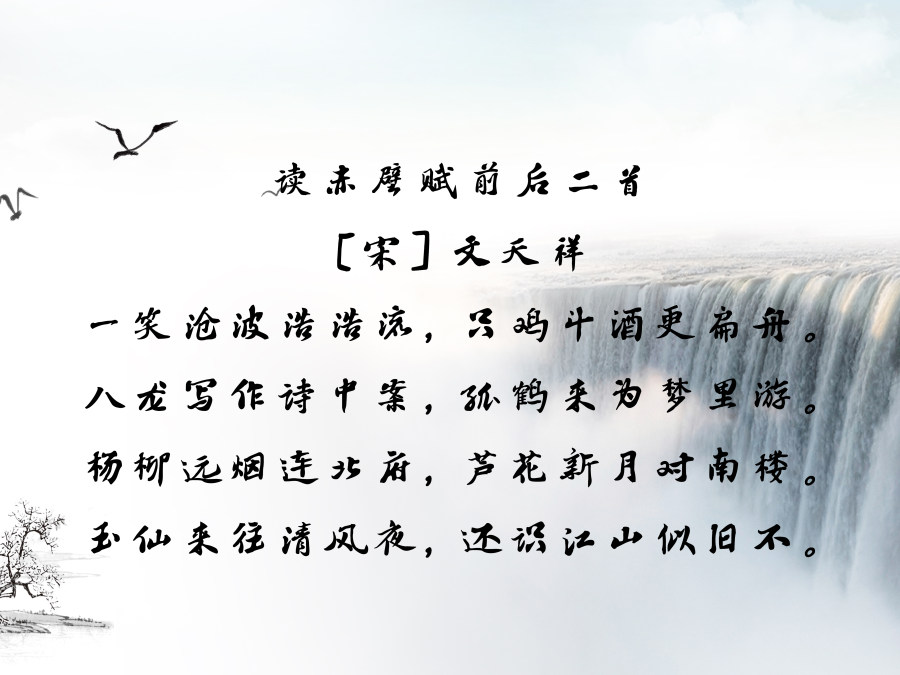
而如果你是想要传播一个严肃的消息,你就可以通过运用一些比较工整的字体来营造端庄的气氛。在版式设计上也是如此,命令指令型消息可以通过用严谨的版式设计来表达,如果想要传播一些娱乐性的消息,那么你就可以创造性的进行版式设计。因此,想要为信息进行润色,大家可以从字体与版式设计来进行改变。
通过前面的内容大家也了解到处在一个信息时代,因此,人人都是信息的传播者、接收者,人人也都需要用到字体与版式设计,独特的字体与版式设计字体合集能够让你的信息的接受度更高,所以人们在提高字体与版式设计的水平上也下了功夫,大家也可以通过义启字库搜索字体,学习排版知识,让自己的信息更具可读性。